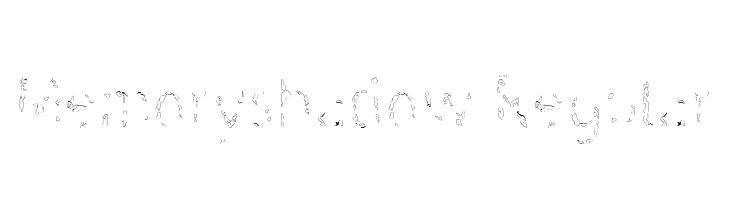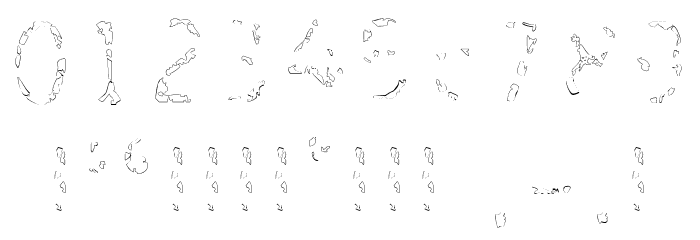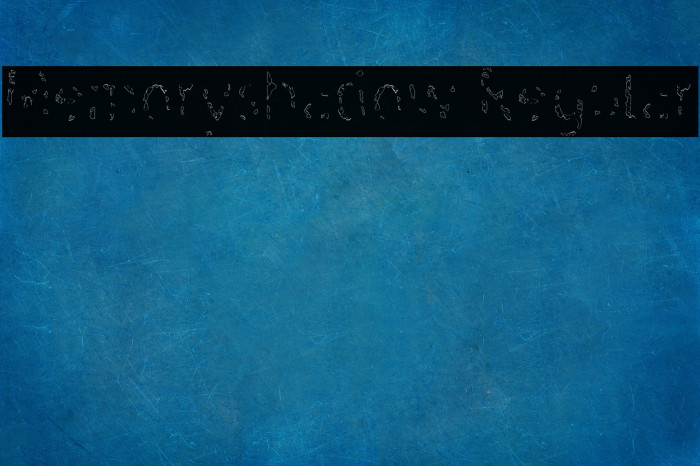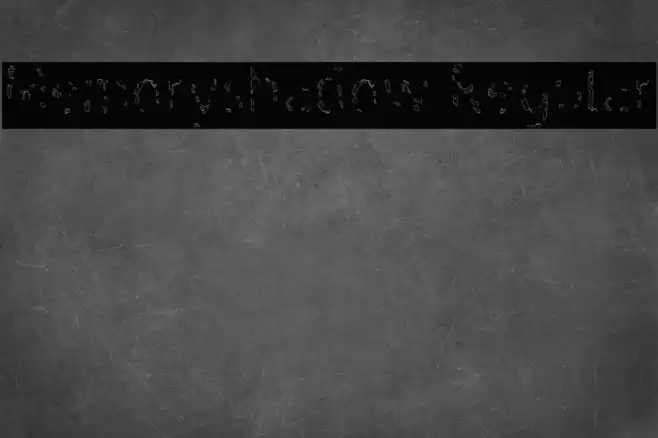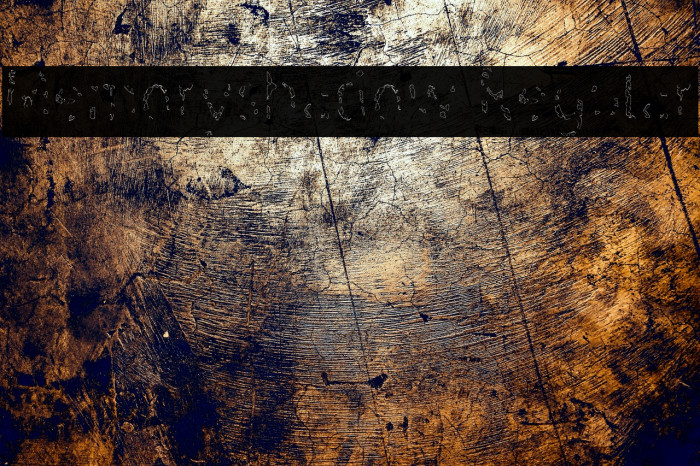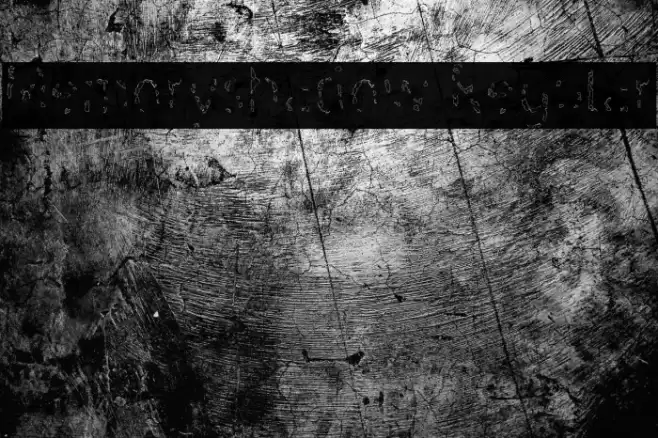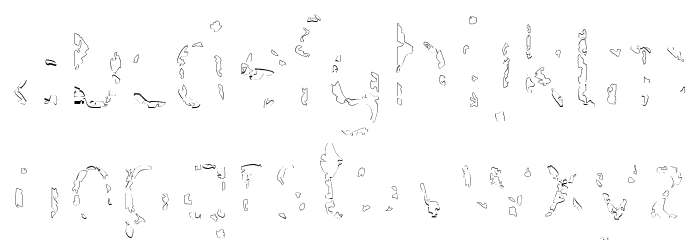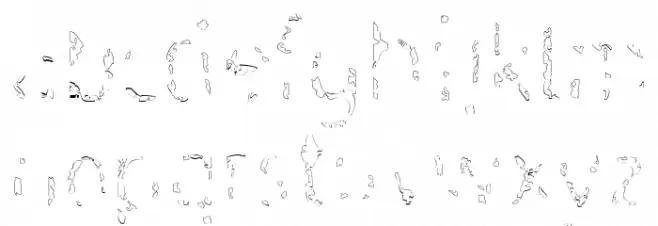
Memoryshadow Regular Font
✎ Distorted Eroded
| Estilo geral | Modern, Artistic |
| Caso de uso | Headlines, Artistic projects, Branding |
| Projetos propostos | Ideal for album covers, posters, artistic projects, and branding that seeks a modern, edgy look. |